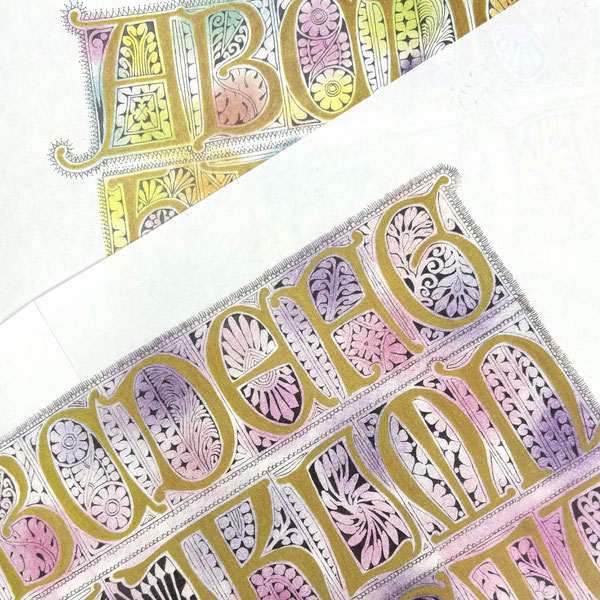
5、6月のおすすめレッスンではフィリグリーとセルティックノッツを行いました。
さて、セルティックノッツは生徒様による優秀作品をご紹介いたしましたので、今回はフィリグリーの素敵な生徒様作品をご紹介差し上げます。
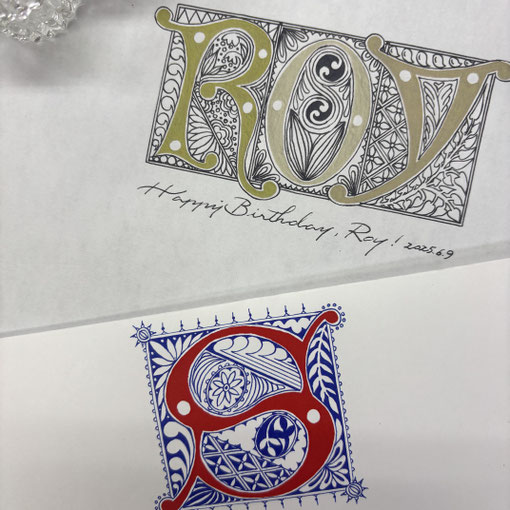
フィリグリーの基本は上のSのように文字を赤にする場合は、周囲の装飾はブルー。文字をブルーにした場合は周囲の模様は赤で描きます。
フィリグリーは15、6世紀に書かれた写本装飾です。基本は大切に縞柄も現代的にさまざまな色彩でアレンジを楽しんでいただくこともできます。
上の画像はY講師によるもので、下の画像はT講師によるものです。
お二方ともにまずは伝統に則った作品を制作された上、伝統にとらわれない色彩や着色方法で、素晴らしい作品を作ってくださいました。
細部まで丁寧に製作されており、素晴らしいものです。
他の生徒様もこの機会に今後、さまざまなデザインにチャレンジしていただきたく存じます。